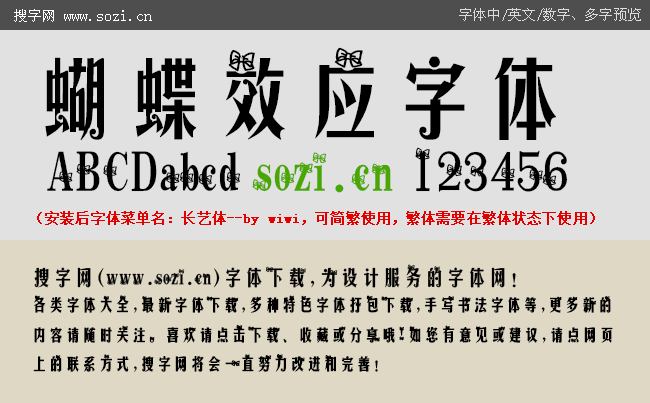
蝴蝶效應(yīng)字體
搜字網(wǎng)給大家提供一款蝴蝶效應(yīng)字體手機(jī)中文字體下載。這款手機(jī)字體是在漢儀長(zhǎng)藝體筆畫(huà)間插入了卡通蝴蝶圖案。長(zhǎng)藝體既有黑體的粗壯醒目,又有宋體的秀美柔和,加上藝術(shù)性的圓球形點(diǎn)、起筆如蝌蚪形的頓點(diǎn)、螺螄轉(zhuǎn)似的小鉤,配以修長(zhǎng)的字形,如少女般婷婷玉立,裊娜動(dòng)人,美觀而不落俗套。加入了卡通圖案后又增添了藝術(shù)性,特別適合喜歡手機(jī)字體個(gè)性一些的朋友在手機(jī)上安裝使用。